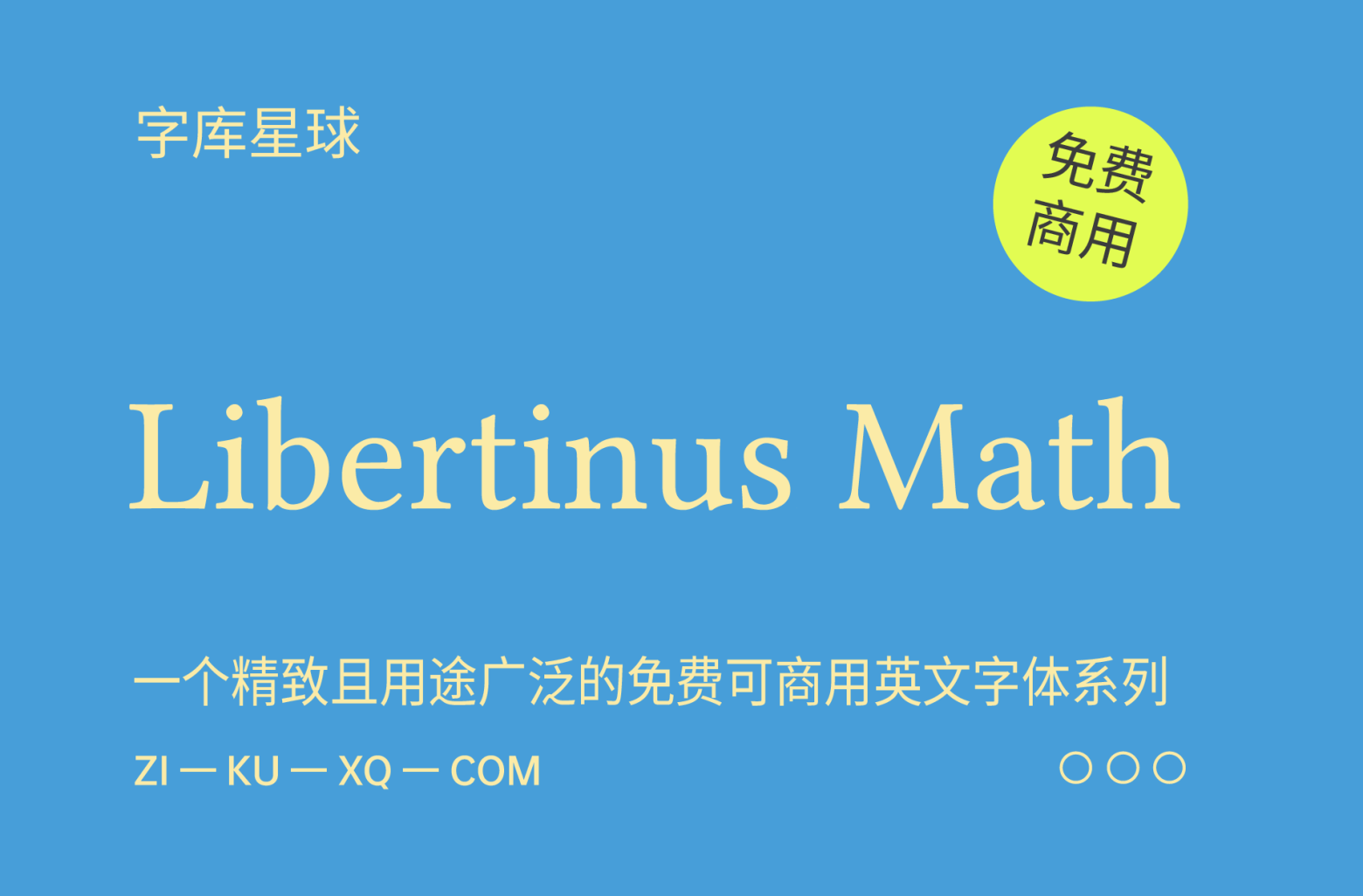
Libertinus Math
Linux Libertinus 是一个精致且用途广泛的免费可商用英文字体系列,它是著名的 Linux Libertine 和 Linux Biolinum 字体的一个分支。Libertinus 旨在提供更完善、更精致的替代方案,它改进了排版细节,并增强了与现代排版系统的兼容性。它包含从衬线到无衬线以及等宽字体的各种样式,适用于各种专业和学术应用。此外,它还广泛支持 Unicode,包括数学符号、希腊文、西里尔文和其他文字,使其成为学术出版和技术文档的热门选择。
Libertinus 字体系列的一大优势在于其对质量和开源可访问性的重视。它使用 FontForge 等现代字体开发工具开发,并由活跃的社区维护,得益于间距、字距和微调的持续改进。Libertinus Serif 是最受瞩目的字体,其外观经典而精致,令人联想到传统的书籍字体;而 Libertinus Sans 则提供了简洁、现代的风格。
此外,Libertinus Mono 则是一款优雅的等宽字体,适用于编码和终端应用程序。凭借其广泛的字符支持和对排版精度的严格把控,Linux Libertinus 仍然是寻求专业级品质的免费开源字体的用户的理想之选。
Libertinus Math